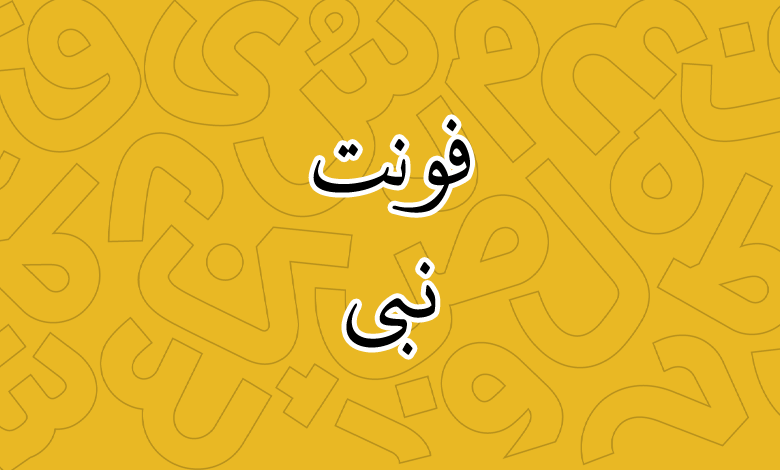
فونت نبی (Nabi)
فونت نبی (به انگلیسی: Nabi) از سری قلم‌های آزاد مناسب برای استفاده در متون بلند است که از یک وزن معمولی Regular پشتیبانی می‌کند. از این فونت می‌توانید برای مطبوعات و همچنین صنعت چاپ به‌ویژه برای کتاب استفاده کنید. در ادامه با دانلود فونت فارسی نبی همراهتان هستیم.
فونت نبی توسط حسین زاهدی با سبک خوشنویسی طراحی شده است. کشیدگی خاص حروف همراه با دندانه‌ها و چشمی‌ها در این فونت آن را به قلمی نمایشی عالی تبدیل کرده است. در تصویر زیر پیش‌نمایش این فونت را می‌بینید.
فونت فارسی نبی از سبک خوشنویسی بهره می‌برد که از زبان فارسی و عربی پشتیبانی می‌کند. گلیف‌های این فونت در بخش کشیدگی حروف و خطوط عمودی با اندازه بیشتر هستند تا ظاهر فونت نمایشی باشد. همچنین به مقدار کمی ظاهر فونت ایتالیک شده است.
از این فونت می‌توانید در موارد زیر استفاده کنید:
• متون بلند
• استفاده در کارهای فرهنگی، هنری و مذهبی
• مناسب برای متن کتاب به‌ویژه تاریخی و داستانی
• استفاده در چاپ بنر و بیلبوردهایی که موضوعات فرهنگی دارند
• استفاده در استوری و پست شبکه‌های اجتماعی
فونت nabi از زبان انگلیسی پشتیبانی نکرده و فاقد گلیف‌ها برای زبان لاتین است. در زبان‌های لاتین نیاز به استفاده از فونتی دیگر دارید.